【2026年版】Webサイトにおすすめのフォント34選!ホームページの目的別の選び方も解説
ホームページのリニューアルを検討する際、デザインやコンテンツと同様、「フォント」の選択も非常に重要であることをご存知でしょうか?
多くの場合、訪問者が最初に目にするのは、テキスト情報です。どのフォントを使うかによって、サイト全体の印象や情報の伝わりやすさが大きく変わります。
また、日本語フォントの選択肢は以前に比べて格段に増えています。無料で使えるWebフォントも充実し、サイトの目的に合わせた最適なフォント選びが可能になりました。しかし選択肢が多いからこそ、「どのフォントを選べばいいのか」という悩みも深くなっているのではないでしょうか。
この記事では、ホームページにおけるフォントの重要性から、サイトの目的別に最適なフォントを選ぶポイント、そして具体的なおすすめフォントまで、分かりやすく解説します。本記事がホームページのフォント選びの参考になれば幸いです。
Webサイトでフォント選びが重要なのはなぜ?
冒頭で触れたとおり、フォント選びはサイトの成功を左右する重要な要素です。
ユーザーがストレスなく情報を理解するために、フォントの「可読性の高さ」が大きく影響します。読みやすいフォントは、ユーザーが内容をスムーズに把握し、サイトに長く滞在してもらう助けとなります。特にスマートフォンなど小さな画面での閲覧が増えている現在、モバイル環境での読みやすさは非常に重要です。
また、文字は情報を伝えるだけでなく、「視覚的なイメージ」においても重要な役割を果たしています。 例えば、「明朝体」のようなセリフ(文字の端にある飾り)のあるフォントは、伝統的で上品な印象、「丸ゴシック体」なら親しみやすく柔らかい印象といったように、フォントの種類によって与えるイメージは異なります。フォントはサイトの第一印象を左右し、ユーザーが抱くブランドイメージにも影響を与えるのです。
【目的別】ホームページのフォントを選ぶポイント
ホームページと一言で言っても、その目的は様々です。ここでは、代表的なサイトの種類ごとに、どのようなフォントを選べば良いのか、そのポイントと具体的なおすすめフォントをご紹介します。
【コーポレートサイト】企業の顔となるフォーマルなデザイン
企業の信頼性や安定感を伝えるコーポレートサイトでは、奇抜さよりも、誠実さや品格を感じさせるフォーマルなデザインが求められます。
フォーマルなデザインに適したフォントの特徴
コーポレートサイトに適したフォントには、以下のような特徴があります。
- 整った字形と適度な太さ
- 過度な装飾がなく、読みやすい
- 一貫性のある印象を与える
- 企業の業種や歴史に合った雰囲気
反対に、「過度に装飾されていて、可読性が低い」「カジュアルすぎる」「トレンドに左右されやすい」フォントの使用は避けたほうが良いでしょう。
企業イメージに合わせたフォント選びのポイント
企業のブランドイメージに合わせたフォント選びが重要です。以下に一例をご紹介します。
- 伝統や歴史を重視する企業:明朝体系
- 先進性や革新を重視する企業:モダンなゴシック体系
- 堅実さや安定感を重視する企業:バランスの取れたゴシック体系
特に金融、法律、医療、教育などの分野では、信頼性が最も重要視されるため、明朝体系のフォントが好まれる傾向があります。一方、IT企業やクリエイティブ産業では、モダンでスタイリッシュなゴシック体系のフォントが適していることが多いです。
また、企業ロゴで使用されているフォントとの調和も考慮すべきポイントです。ロゴのフォントと同じファミリーのフォントを使用するか、視覚的に調和するフォントを選ぶことで、ブランドの一貫性を保つことができます。
コーポレートサイトにおすすめのフォント
– – 明朝体 – –
- 游明朝体
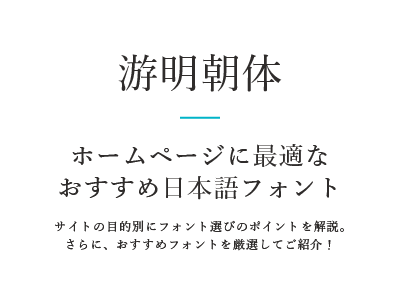
- Noto Serif JP
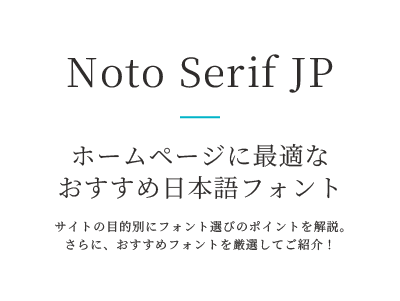
- ヒラギノ明朝
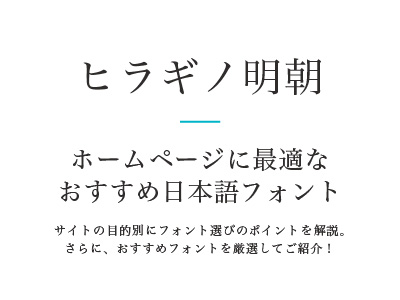
– – ゴシック体 – –
- 游ゴシック
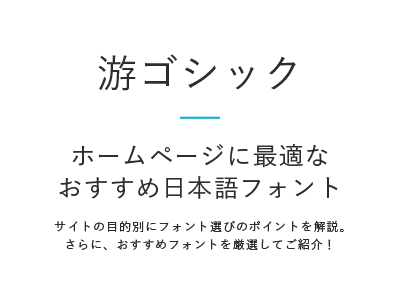
- Noto Sans JP
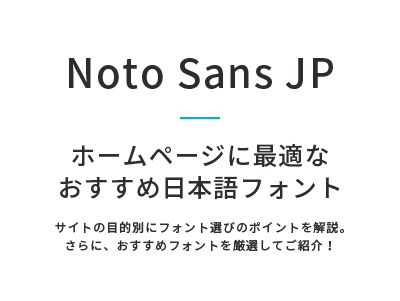
- ヒラギノ角ゴシック
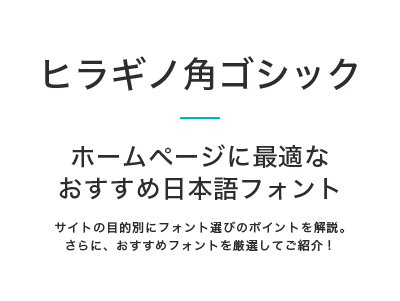
【サービスサイト】信頼感とプロフェッショナルな印象
サービスサイトでは、提供するサービスの専門性や信頼性を伝えつつ、ユーザーにとって親しみやすい印象を与えることが重要です。
信頼感とプロフェッショナルな印象を与えるフォントの特徴
サービスサイトに適したフォントには、以下のような特徴があります。
- 明確な字形と適切な文字間隔
- 長文でも読みやすい
- 専門性を感じさせる適度な格式
- 親しみやすさも兼ね備えている
サービスサイトでは、ユーザーが長時間滞在して情報を収集することが多いため、長文でも読みやすいフォントを選ぶことが重要です。また、サービスの専門性を伝えるために、適度な格式を持ったフォントが効果的です。
サービス内容に合わせたフォント選びのポイント
サービスの性質によってフォント選びのポイントも変わります。下記、主なサービスごとにおすすめのフォントをまとめました。
- 専門的なコンサルティングサービス:信頼感のある明朝体系やセリフ系
- クリエイティブなサービス:個性的でモダンなゴシック体系
- 教育関連サービス:読みやすさを重視したゴシック体系
- 医療・健康関連サービス:清潔感のある丸ゴシック系
サービスサイトにおすすめのフォント
– – 明朝体 – –
- しっぽり明朝
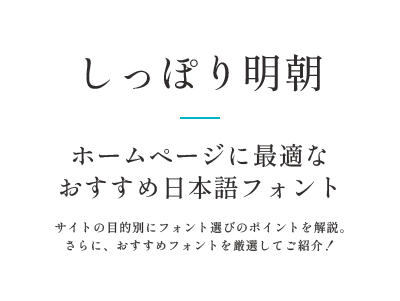
- 源ノ明朝
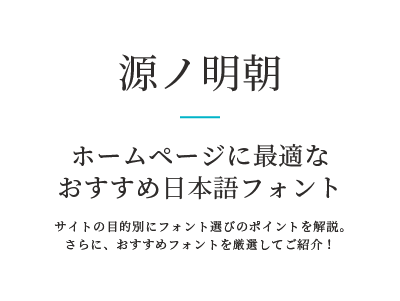
– – ゴシック体 – –
- A1ゴシック
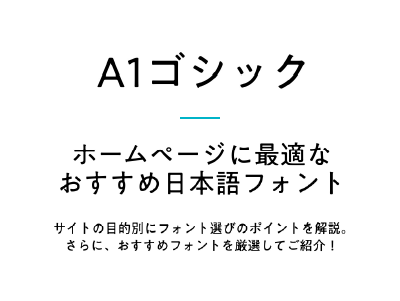
- 源ノ角ゴシック
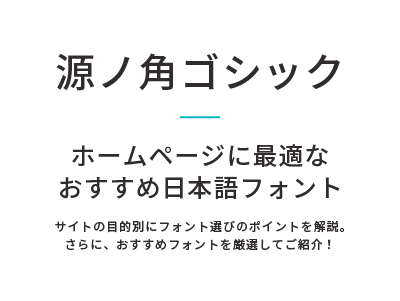
- 筑紫オールドゴシック
【ECサイト・LP】購買意欲を高める視認性とデザイン性
ECサイトやランディングページ(LP)では、商品やサービスの魅力を効果的に伝え、購買意欲を高めることが重要です。そのためには、視認性の高いフォントやユーザーの目を引くデザイン性の高いフォント選びが求められます。また、2025年時点で、ECサイトへのアクセスの約70%はスマートフォンからと言われています。そのため、モバイル環境での表示を考慮したフォント選びも意識する必要があります。
ECサイト・LPに適したフォントの特徴、選び方
ここでは、「視認性の高いフォント」「デザイン性の高いフォント」「モバイルに適したフォント」の3点に焦点をあて、それぞれ特徴を解説していきます。
1.視認性の高いフォントの特徴
ECサイトでは商品情報を正確に伝えることが最も重要です。特に商品説明や仕様などの詳細情報は、ユーザーが正確に理解できるよう、可読性を最優先に考えるべきです。
商品情報を伝えるコンテンツでは、以下の特徴を持つフォントが適しています。
- くっきりとした字形
- 適切な太さと文字間隔
- 小さいサイズでも読みやすい
- 商品名や価格が一目で分かる明確さ
2.デザイン性の高いフォントの特徴
デザイン性の高いフォントは、ユーザーの購買意欲を高める力を持っています。デザイン性の高いフォントを効果的に活用することで、商品の魅力を伝える後押しになります。
デザイン性の高いフォントの特徴は、下記のとおりです。
- 商品のイメージに合った雰囲気
- アクセントとなる個性的な見出しフォント
- セール情報や限定商品を強調できる太めのフォント
- ブランドイメージと調和するフォント
3.モバイル対応を考慮したフォント選び
最後に、モバイル環境での表示を考慮したフォント選びのポイントを紹介します。
- 小さい画面でも読みやすいフォント
- 画面サイズに応じて適切に表示されるレスポンシブ対応
- データ容量の軽いWebフォント
ECサイト・LPにおすすめのフォント
– – ゴシック体 – –
- M+ FONTS
- ZEN丸ゴシック
- やさしさゴシック
– – アクセント用 – –
- コーポレート・ロゴ(ラウンド)
- おつとめフォント
【カジュアルなサービスサイト】親しみやすさと個性を表現
カフェや美容室、フィットネスジム、習い事教室など、カジュアルなサービスを提供するサイトでは、親しみやすさや個性を表現することが重要です。ターゲットとなる顧客層に合わせたフォント選びが成功のカギとなります。
親しみやすさと個性を表現するフォントの特徴
堅苦しさを排除した、親しみやすい印象を与えるフォントには、以下のような特徴があります。
- 丸みを帯びた字形
- 適度な遊び心のある装飾
- 温かみを感じさせる線の太さや形状
- 自然な手書き感
特に対面サービスを提供する業種では、店舗の雰囲気や顧客に与えたい印象をフォントで表現することで、ユーザーの期待感を高めることができます。例えば、カフェでリラックスした雰囲気や居心地の良さを感じてもらいたい場合、サービスサイトやSNSだけでなく、カフェメニュー・店内POPなどにも温かみのあるフォントを使用するなどが挙げられます。
ターゲット層に合わせたフォントの選び方
フォントの特徴をふまえ、サービスのターゲット層に合わせたフォントを選ぶことも大切です。下記、具体例です。
- 若年層向け:個性的でトレンド感のあるフォント
- ファミリー層向け:親しみやすく読みやすいフォント
- シニア層向け:可読性を重視した明確なフォント
- 女性向け:柔らかさや美しさを表現したフォント
カジュアルなサービスサイトにおすすめのフォント
– – ゴシック体 – –
- ZEN丸ゴシック
- しっぽりアンチック
- クレー One
– – 個性的なフォント – –
- うつくし明朝体
- はんなり明朝
- 貂明朝(てんみんちょう)
【海外向けサイト】多言語対応とフォントの組み合わせ
グローバルに展開する企業や、インバウンド需要を取り込みたい企業のサイトでは、複数の言語で情報を発信する必要があります。今回は、特に利用頻度の高い英語(欧文フォント)に焦点をあて、日本語フォントと効果的に組み合わせるためのフォント選びのポイントを解説します。